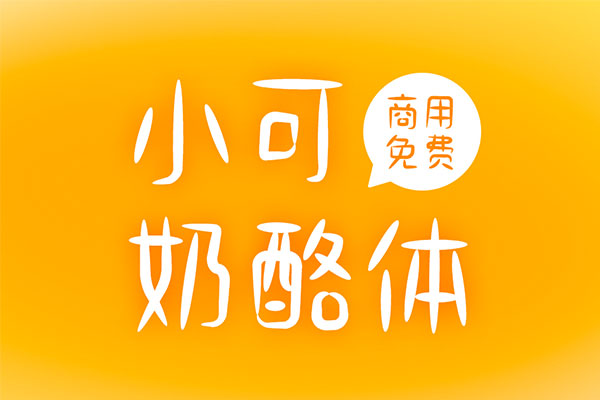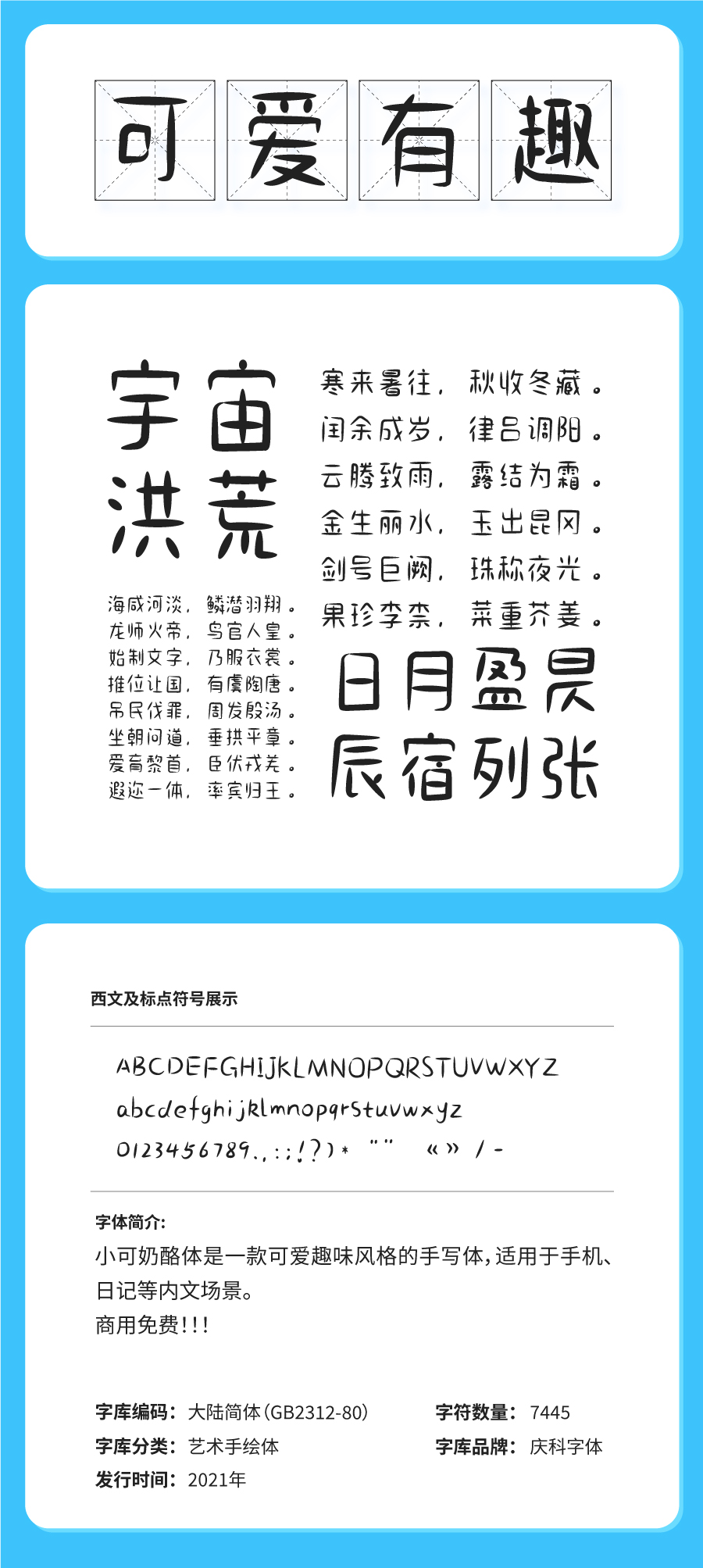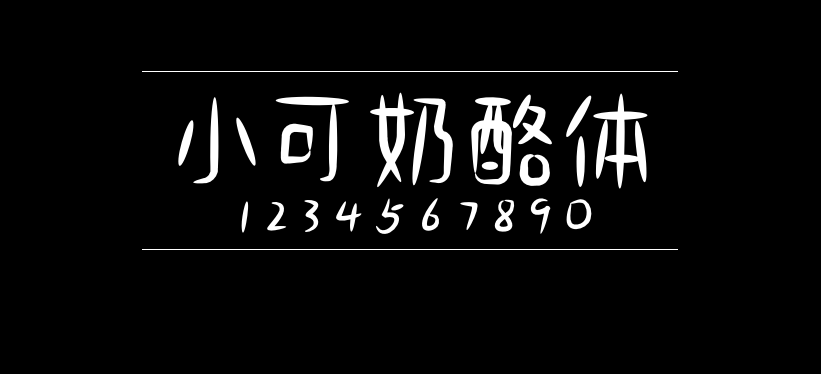
小可奶酪体
小可奶酪体是国内知名字体设计师郑庆科的又一款免费商用字体,自由字体已收录的庆科FS霓虹灯英文体、站酷庆科黄油体 、创客贴金刚体 都是出自郑庆科之手。这次新推出的小可奶酪体是一款设计感很强的手写风格艺术字体,风格轻松随性,充满可爱趣味,可用于手机、日记等内文场景。
小可奶酪体
小可奶酪体字体效果预览
小可奶酪体